Canvaでは、どんなデザインにも使えるようにさまざまな種類のモリサワフォントを取り揃えております。教育用のコンテンツで利用できる教科書体や学参フォント、かわいらしい手書きフォント、Sans Textの丸めの英語フォント、極細フォントなど用途に合わせてお使いください。メッセージカードや寄せ書きなら丸めのフォントが親しみやすくておすすめ。スローガンや表紙の洗練されたデザインなら「じゅん Pro」など細めのフォントがおすすめ。そのほか30種類以上の明朝体、MorisawaゴシックMB101、丸ゴシック体などを含む30種類以上のゴシック体、Morisawa含む20種類のUDフォントもあります。
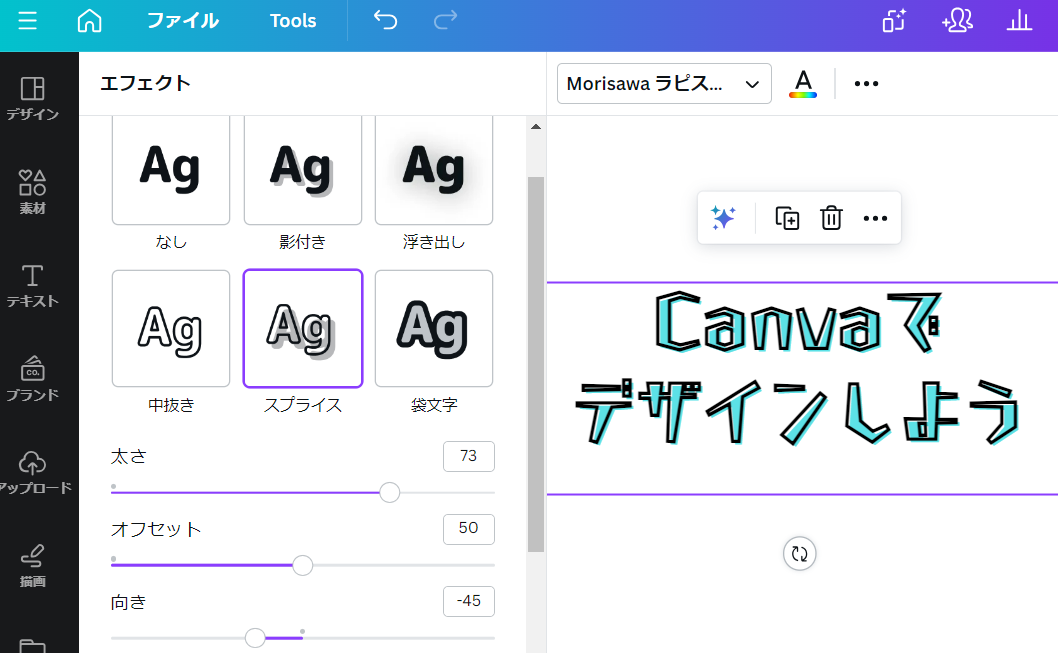
Canvaのエフェクト機能を使えば、モリサワフォントをさらに引き立たせることができます。文字を選択して [エフェクト] をクリックすると、影付き、浮き出し、中抜き、スプライス、袋文字、エコーグリッチ加工、ネオン、背景のエフェクトが選べるようになっています。さらに、湾曲させて文字にゆるやかなカーブを足すこともできます。ロゴにもおすすめのフォントデザインです。ただし、UDフォントは縁取りや影付きなど加工することにより、読みやすさが半減することがあるので使い方に注意しましょう。
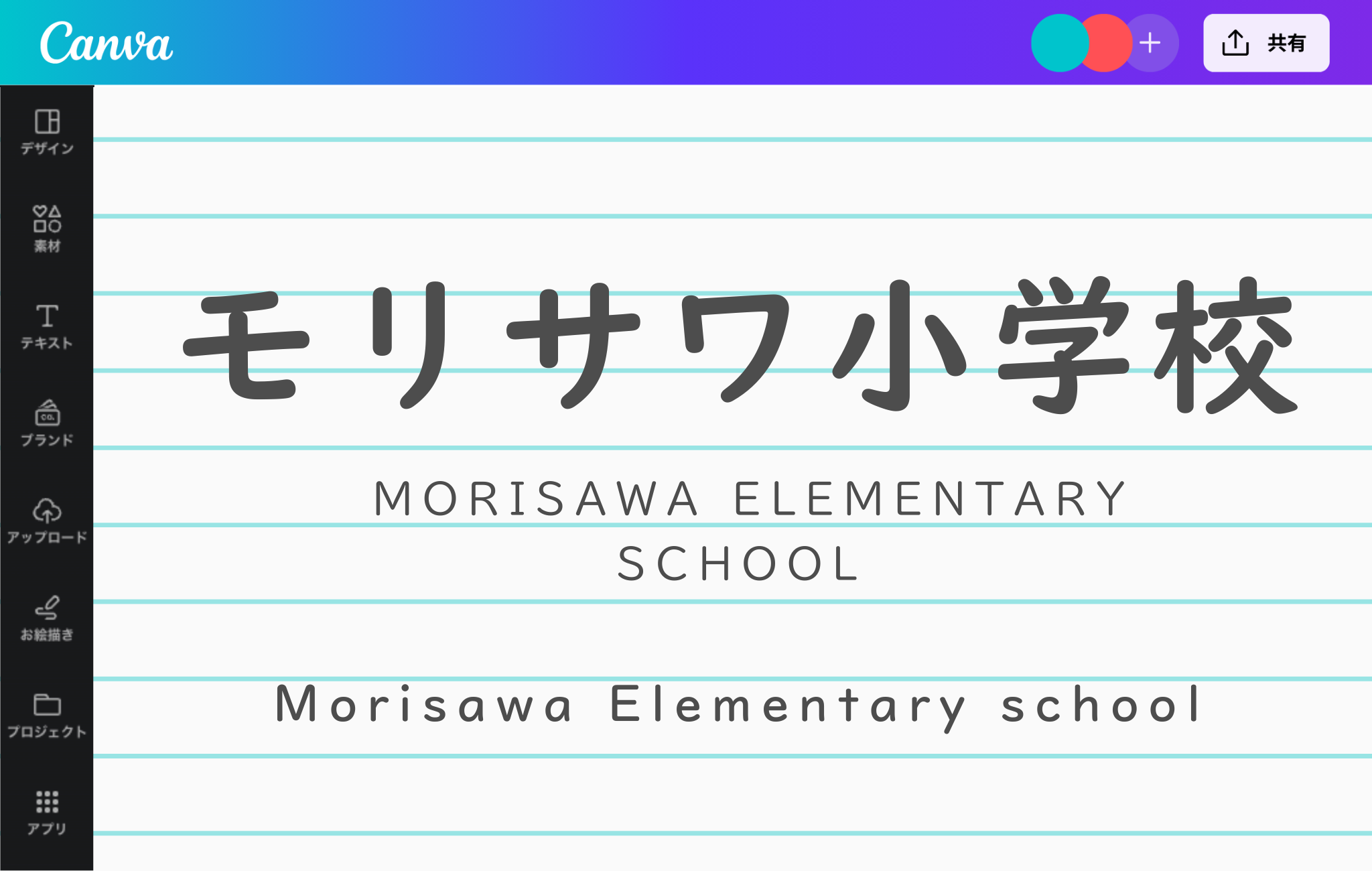
教職員のご要望に応え「UDデジタル教科書体」がさらにバージョンアップして、Canva用オリジナルフォントとして登場しました。ロービジョンやディスレクシアなど読み書きに困難さを抱える方にも読みやすいデザイン作りを、科学的根拠を持ってサポートします。 国語や算数はもちろん、英語の教材づくりでも使いやすく、教えやすい、教科書にも使われている形状のフォントです。
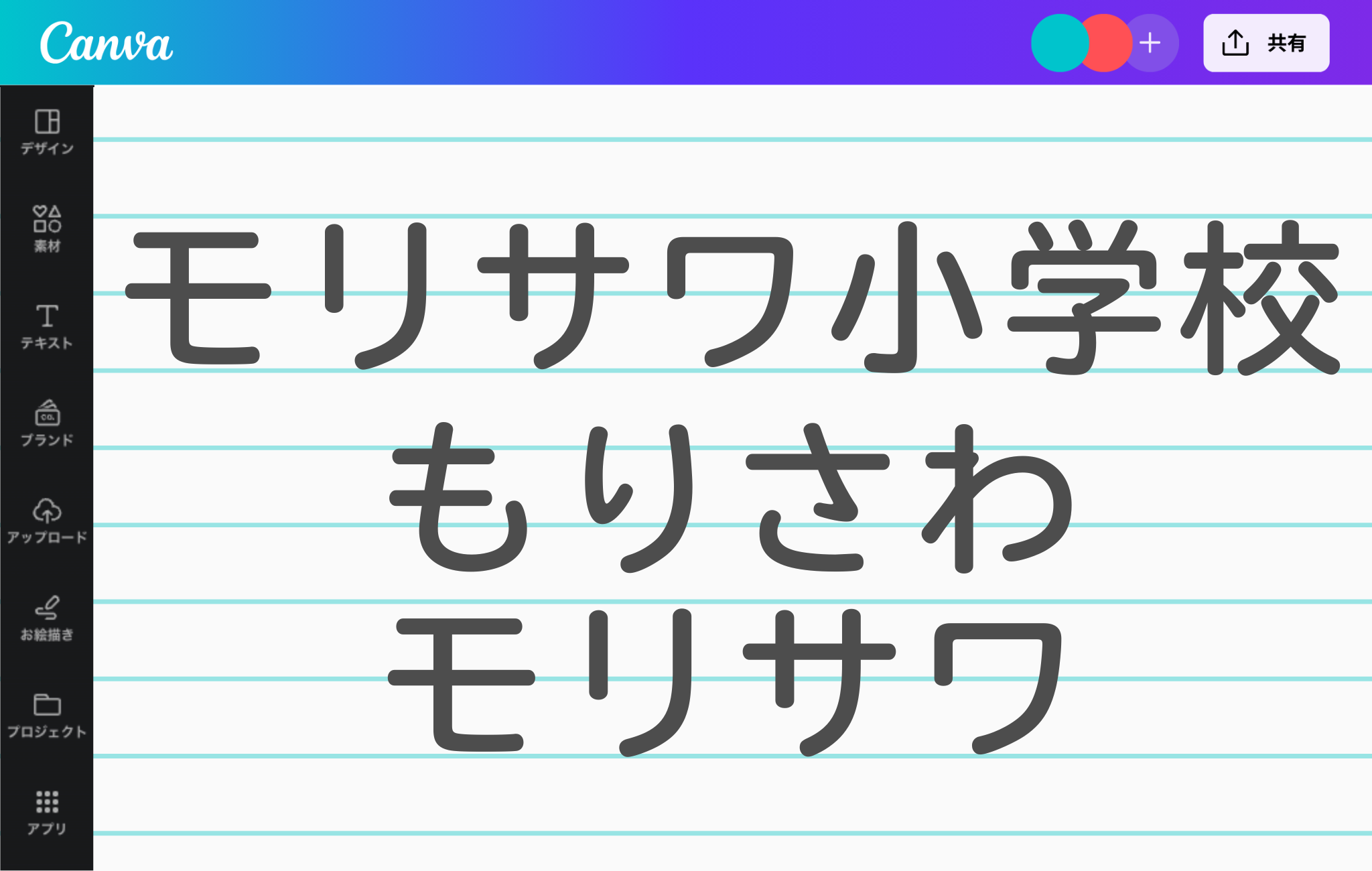
UD学参丸ゴシックは、教科書・教材のために開発された丸ゴシック体です。全ての和文文字(ひらがな・カタカナ・漢字)は学習指導要領の字形に準拠していて、ひと文字ひと文字が大きく見えるように作られています。「UDデジタル教科書体NPL」と並んで、読み書きに困難さのある児童・生徒を含む多くの子どもたちの学習を助けるフォントです。子どもたちの発達段階や目的に合わせて使い分けることができます。
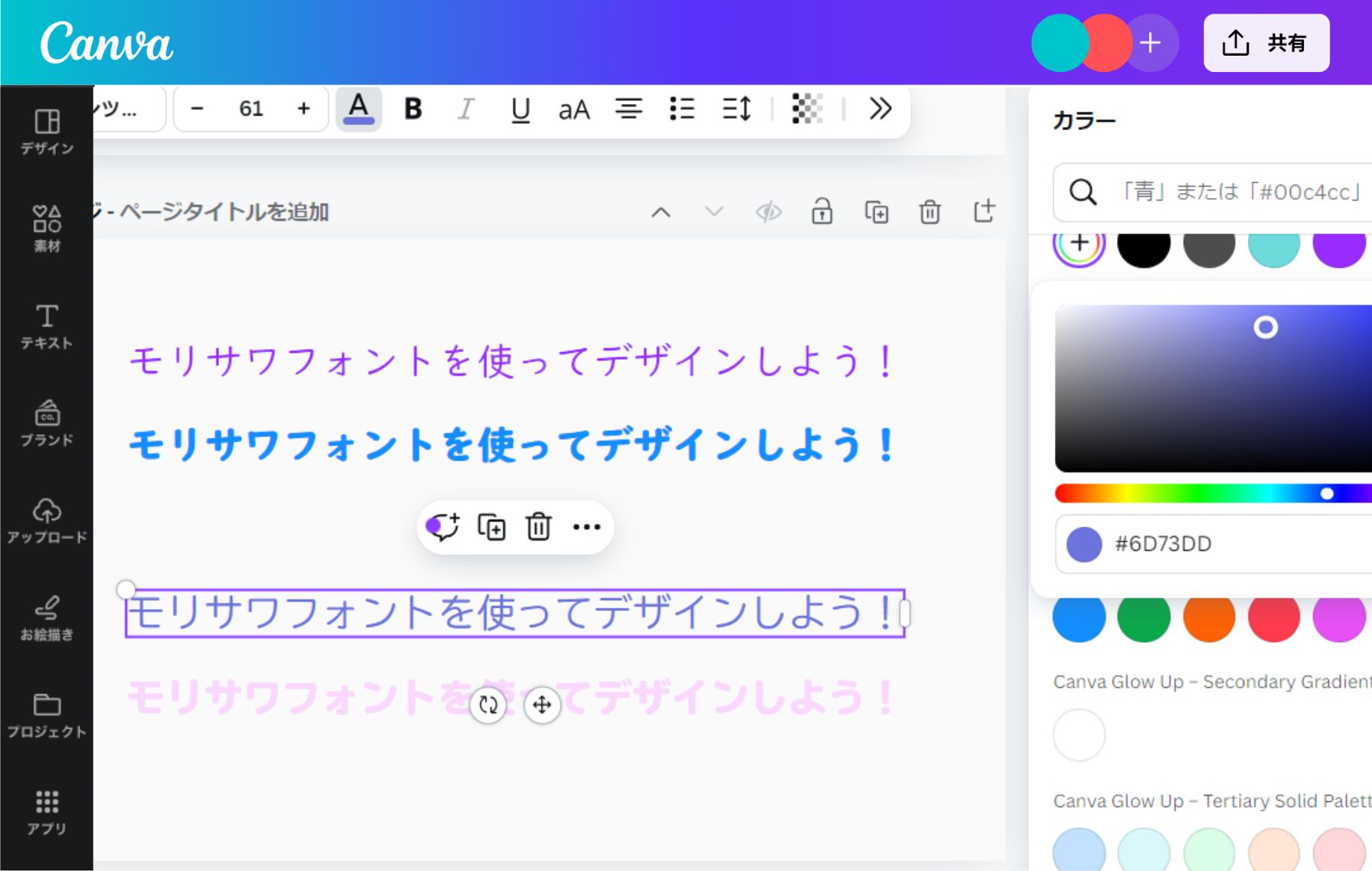
Canvaのカラーパレットを使えば、モリサワフォントの文字をどんな色にも編集できます。パステルやニュアンスカラー、オフニュートラルカラーなど、通常見つけるのが難しい色も取り揃えています。始めから指定のカラーを追加するならカラーコードの入力を。「+」のアイコンを押してカラーを追加し続けることが可能です。ブランドカラーが決まっているなら、ブランドキットを活用するのもおすすめ!
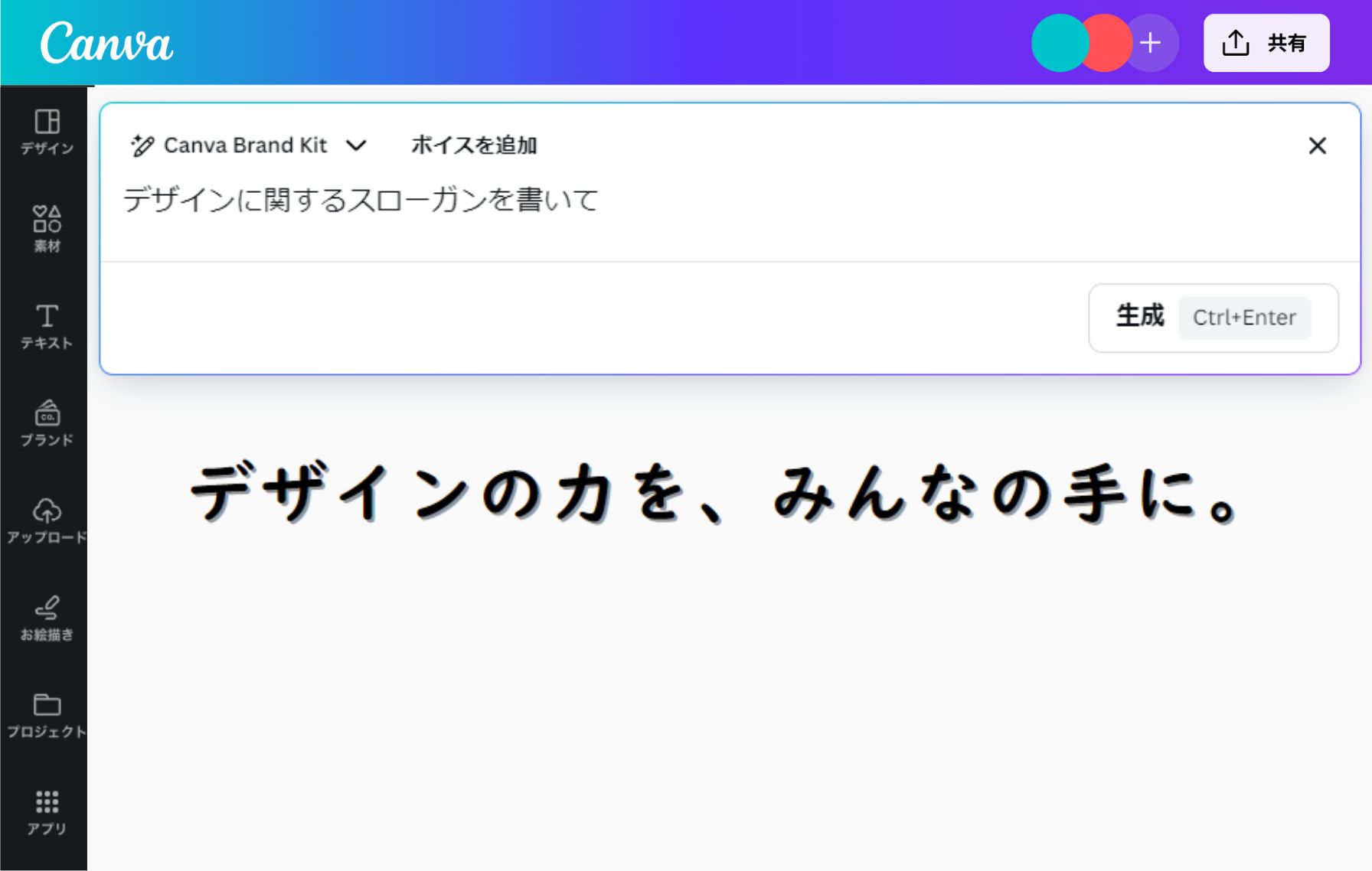
Canvaのマジック作文を使えば、自動でおしゃれなスローガンや文章を生成できます。インスタ広告のキャッチコピーやポスターのスローガン、プレゼンテーションのタイトルにも。普段なかなか思いつかないようなクリエイティブな文章がサクサクっと作成できます。AI生成ツールを活用して出来上がった文章はおしゃれなモリサワフォントに変換!素早く文章が書ければ、フォント選びや背景デザインにもっと時間を費やすことができるでしょう。